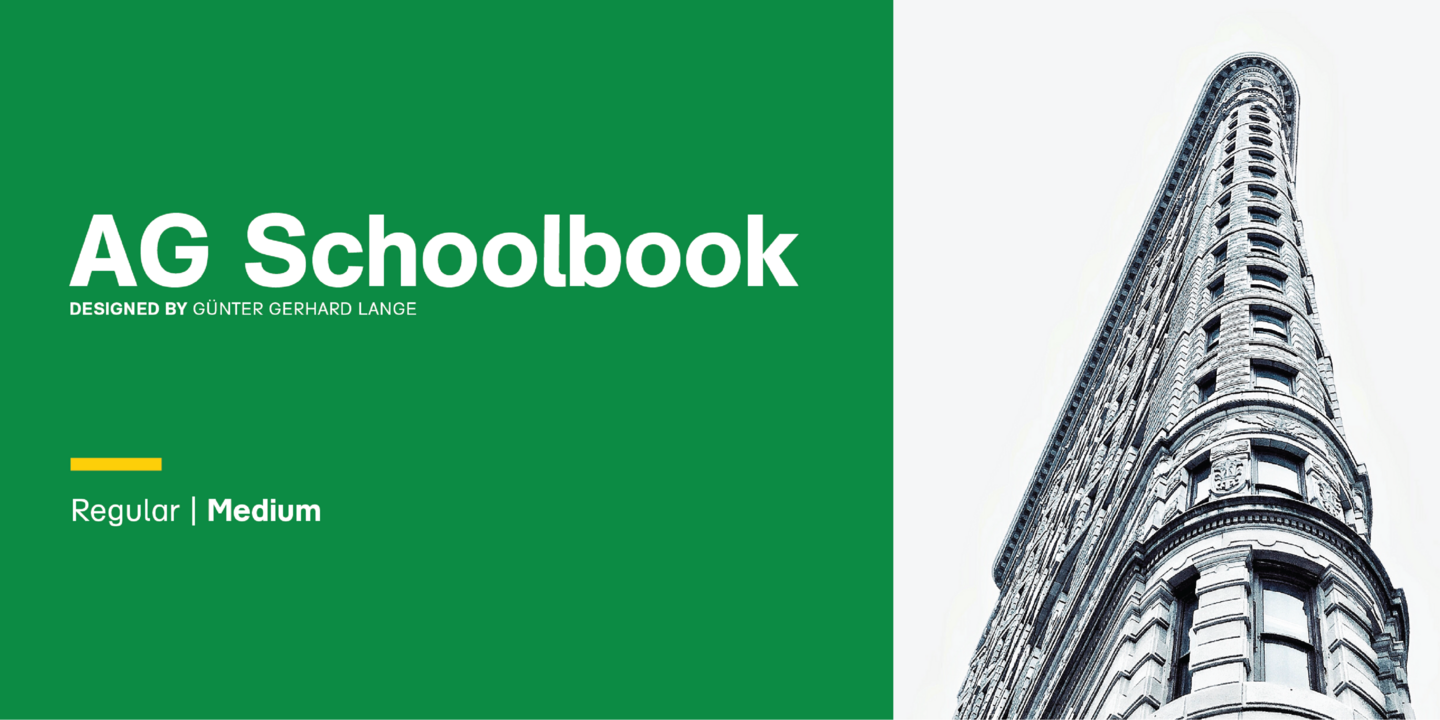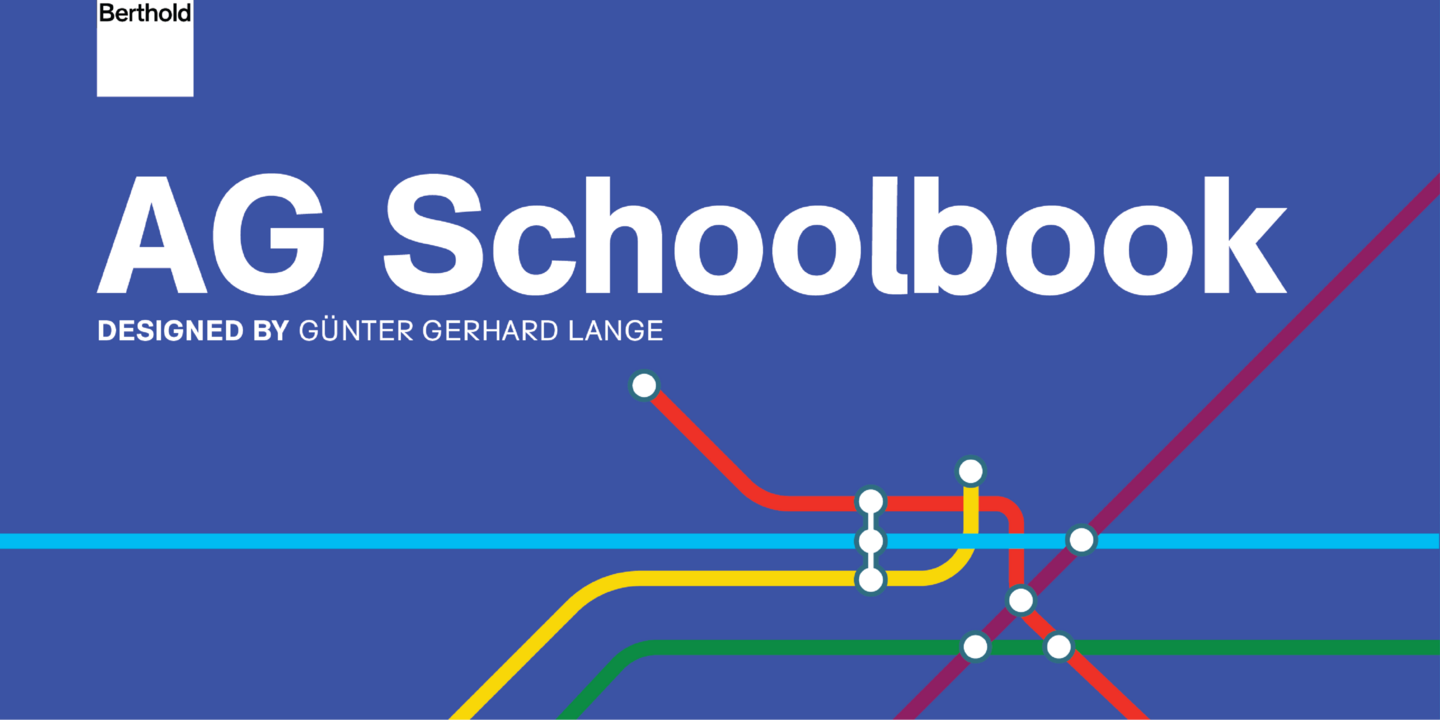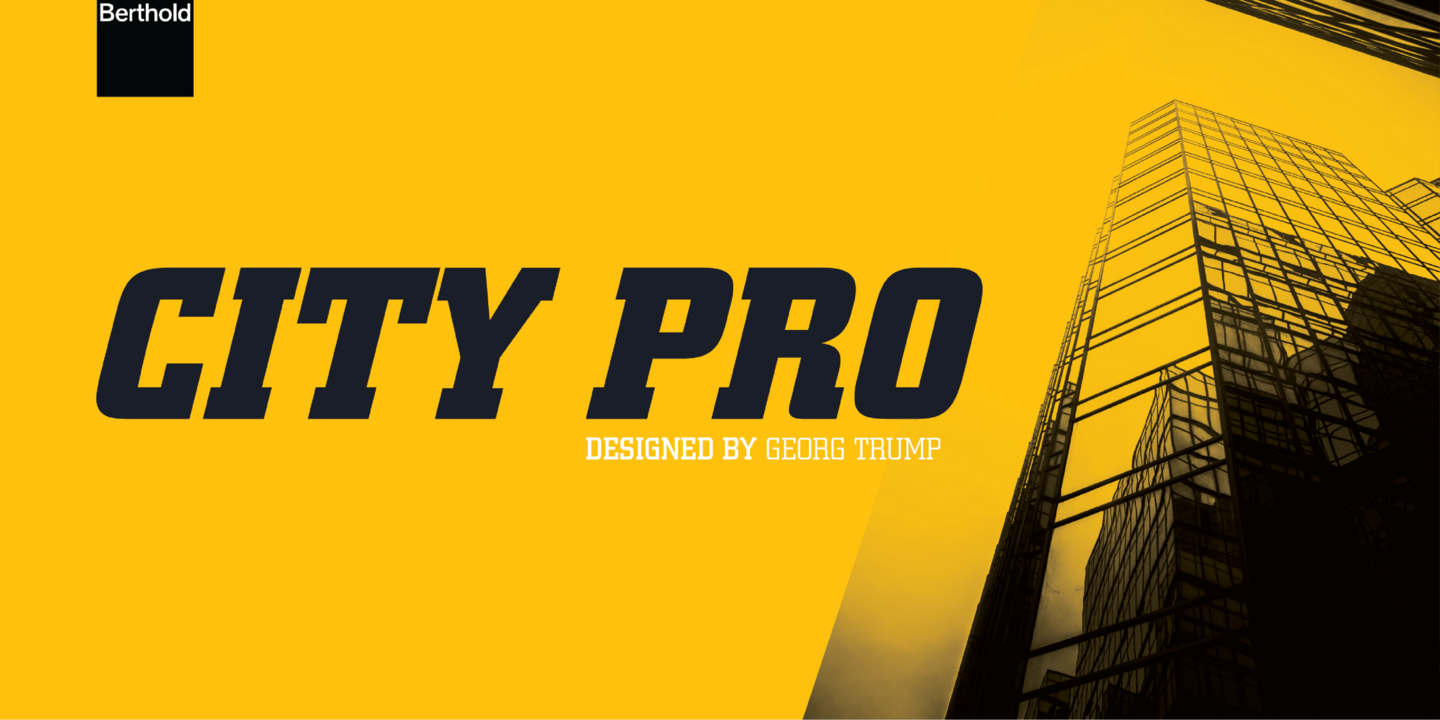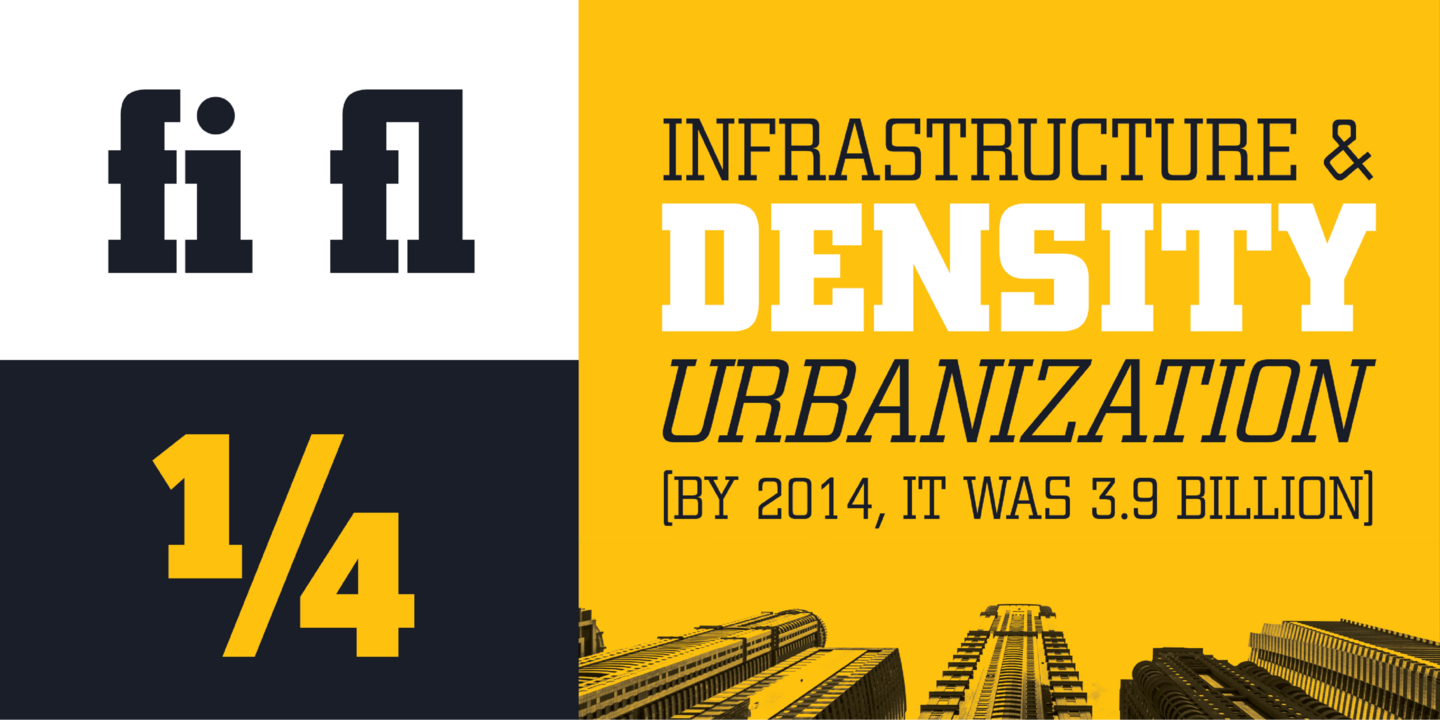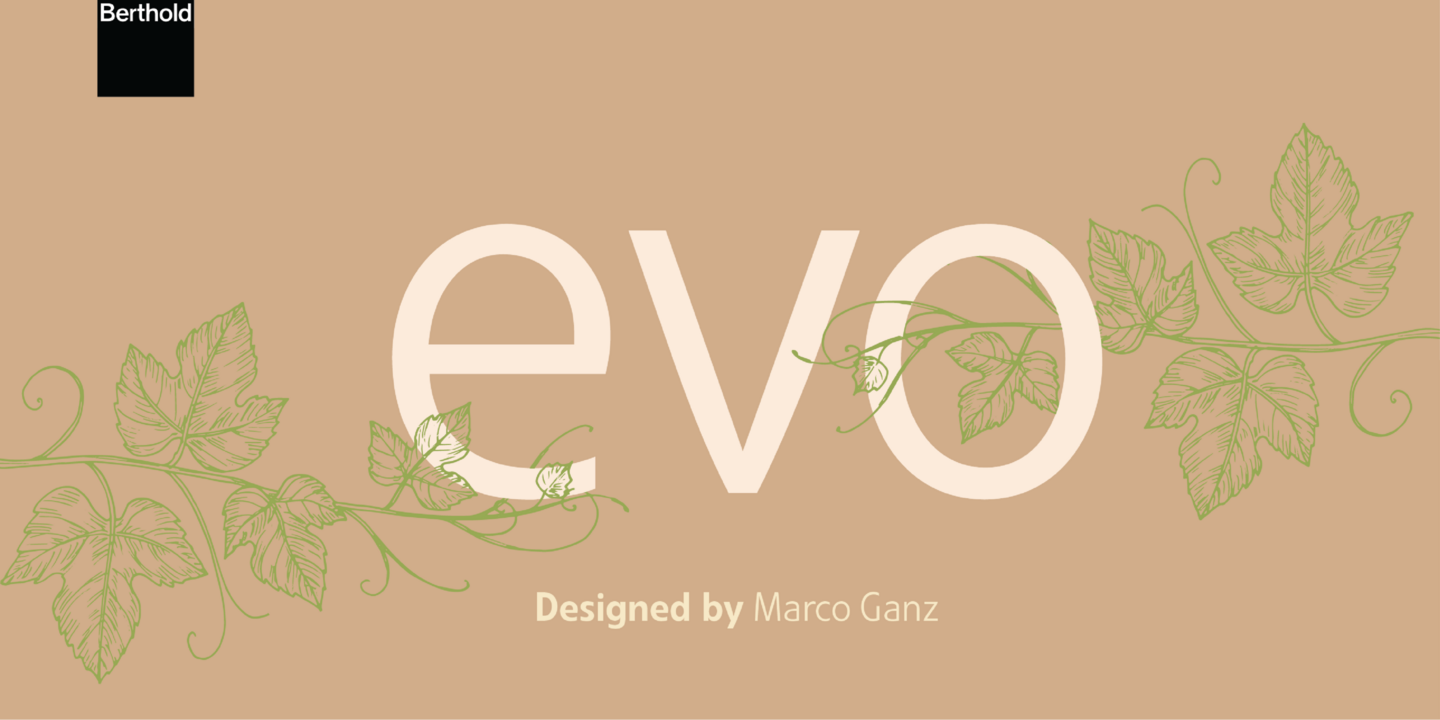
Polices de Berthold.
H. Berthold a été fondée en 1858 par Hermann Berthold à Berlin, initialement pour fabriquer des règles d'imprimerie en laiton. Suivante En 1893, elle a commencé à couler des caractères métalliques à la main et, au cours des 25 années suivantes, elle est devenue l'une des plus grandes fonderies de caractères au monde. Après la Seconde Guerre mondiale, Berthold a mis au point des équipements de composition métallique à la machine et a commercialisé sa première photocomposeuse en 1950.
H. La famille de caractères la plus célèbre de Berthold AG, Akzidenz-Grotesk, a été publiée en 1896. Au cours du XXe siècle, la fonderie de caractères Berthold a développé la collection Berthold Exklusiv, plus de 700 caractères créés uniquement pour la fonderie. Les familles de caractères Agora, Barmeno, Berliner Grotesk, City, Formatta, Imago, Poppl-Laudatio et Quadriga constituent un échantillon de ces créations.
Familles populaires de Berthold Police .
Hans Reichel a créé Barmeno pour H. Berthold en 1983. Ce caractère sans empattement arrondi possède des caractères individuels distinctifs, mais lorsqu'il est considéré dans un corps de texte, il est chaleureux, harmonieux et lisible. Le Barmeno est souvent utilisé pour des textes publicitaires, des mises en page de magazines et de sites web. La graisse extra grasse est particulièrement adaptée aux titres qui attirent l'attention.
Berthold a publié pour la première fois Akzidenz-Grotesk en 1896. Le dessin provient de la lumière Royal Grotesk de Ferdinand Theinhardt, qui a également fourni les graisses régulières, moyennes et grasses. Au fil des ans, Berthold a élargi cette famille extrêmement populaire et polyvalente. AG Super a été développé en 1968 par Guenter Gerhard Lange et constitue un excellent choix pour les titres. En 2001, Guenter Gerhard Lange a ajouté d'autres graisses pour Berthold, notamment Super Italic et Extra Bold italic.
Günter Gerhard Lange a redessiné la famille Akzidenz-Grotesk et H. Berthold l'a publiée sous le nom de AG Schoolbook en 1983. Cette version plus contemporaine de l'Akzidenz-Grotesk propose des caractères alternatifs distinctifs pour a, k, l, u, y, G, I, J, K, M et R. L'AG Schoolbook est réputé pour sa clarté et sa lisibilité.
Conçus pour attirer l'attention et avoir un impact dans la publicité, les premiers égyptiens ou slab serifs sont apparus au début de la révolution industrielle (années 1800). Ils ont connu un regain de popularité après la Première Guerre mondiale et, en 1930, Berthold a publié le City de Georg Trump, un dessin rectangulaire distinctif qui évoque un sentiment sportif et urbain.
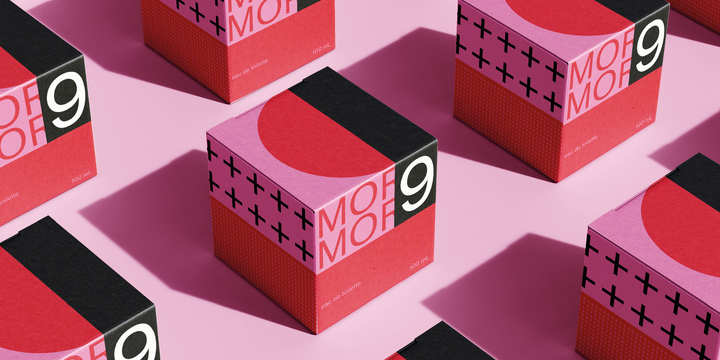
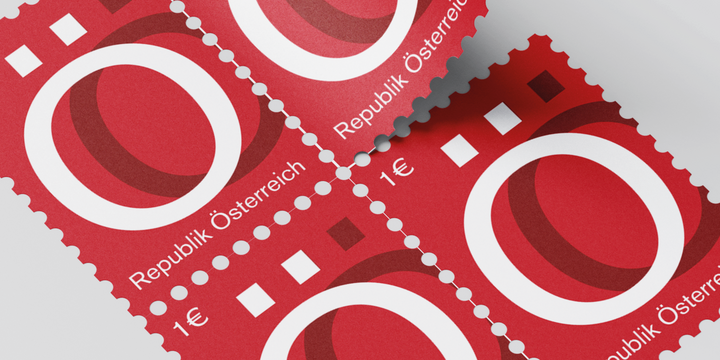
En 1997, Berthold Types, une société basée à Chicago, a acquis les droits d'auteur, la marque et les droits de conception associés à la collection Berthold Exklusiv. Günter Gerhard Lange, directeur artistique de Berthold de 1961 à 1990, était responsable de la majeure partie de la création et de la production de la collection Berthold Exklusiv. En 1991, Bernd Möllenstädt a succédé à Lange en tant que directeur typographique de la collection Berthold Exklusiv et a dirigé la numérisation des dessins.
En 2022, Monotype a acquis la bibliothèque de caractères historiques de Berthold. L'intendance de Monotype permettra d'accroître la visibilité mondiale de l'inventaire de Berthold, de célébrer son héritage et de mettre ces caractères importants entre les mains d'un plus grand nombre de créateurs.
Né en 1831, Hermann Berthold était le fils d'un imprimeur de calicots. La plupart des imprimeurs typographiques allemands et de nombreux imprimeurs étrangers passaient leurs commandes à Berthold. Ses produits sont devenus si populaires que les imprimeurs ont popularisé l'expression "Aussi précis que le laiton de Berthold". Hermann Berthold a dirigé la fonderie Berthold jusqu'en 1888.
Designer
Günter Gerhard Lange
Le célèbre maître-artisan Günter Gerhard Lange est né le 12 avril 1921 à Francfort-sur-l'Oder, en Allemagne. En 1961, Berthold a nommé Lange directeur artistique. Lange a été nommé au conseil d'administration de Berthold en 1971, confirmant ainsi l'importance de la typographie chez Berthold. En tant qu'instigateur du programme typographique de Berthold de 1961 à 1990, Lange était responsable de la création, des normes de production méticuleuses et de l'attention portée à la qualité de chacun des Exklusivs de Berthold.
Designer
Albert Boton
Né en 1932, Albert Boton a étudié le graphisme et suivi des cours de calligraphie auprès d'Adrian Frutiger. Plus tard, il a travaillé comme apprenti typographe à la fonderie Deberny & Peignot à Paris, sous la direction d'Adrian Frutiger. Berthold a publié Boton (1986) et Agora (1990) dans le cadre du programme Berthold Exklusivs.
Dieter Hofrichter
Dieter Hofrichter, assistant et protégé de longue date de Günter Gerhard Lange, est né à Mannheim Baden-Württemberg, en Allemagne. En 2000, Berthold a publié une œuvre commune de Lange et Hofrichter, un type écossais appelé "Whittingham". Parmi les autres contributions de Hofrichter, citons la publication de l'Akzidenz-Grotesk amélioré et la publication du Futura BQ.